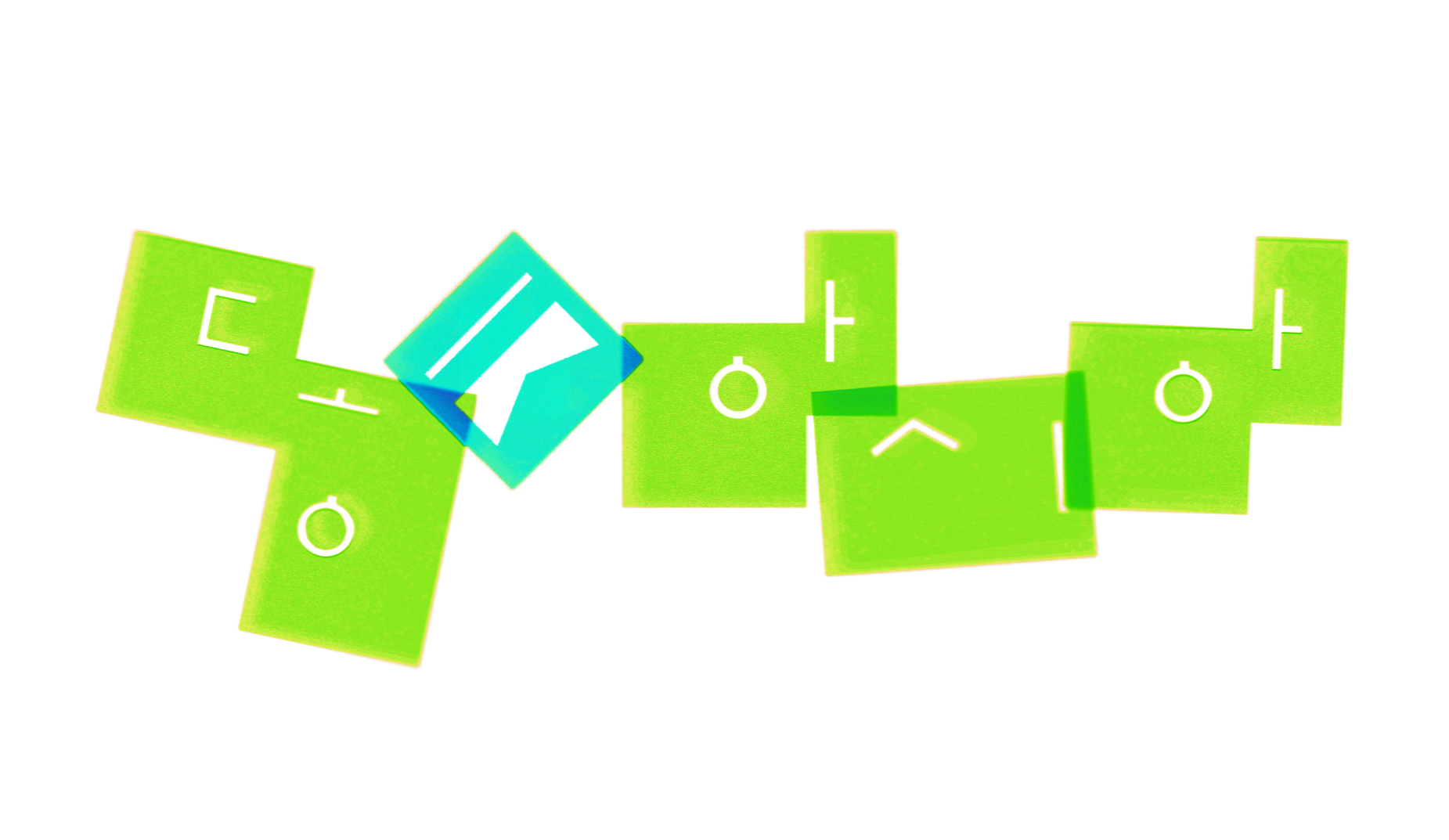
【동아시아(Asia) 친구들 문자와 함께 써요.】 〈친구체Chingu〉는 한자문화권 전각문자와 다국어 조판하기 위한 풀어쓰기 탈네모꼴 서체입니다. 한자문화권의 다른 전각 문자와 탈네모꼴 한글을 혼합조판 하기 위한 고민에서 시작합니다. 전각 공간과 탈전각 공간의 논리가 충돌해서 만드는 기분 좋은 노이즈를 만나보세요. 〈친구체Chingu〉는 이를 드러내기 위해 흑과 백을 반전한 블록(block)형 서체입니다. 또한 포함된 공백 글립을 통해 띄어쓰기 역시 블록으로 설정할 수 있습니다. 전각문자와의 다국어 조판이 필요한 포스터, 제목, 표지 등의 작업에 활용해 보세요. 이질성은 서로를 밀어내는 성질이 아닙니다. 문자가 만드는 관계의 아름다움!
친구체
Chingu
친구체는 한자문화권 문자와의 혼합 조판을 위해 설계된 전각·반각 모듈형 탈네모꼴 서체입니다. 탈네모꼴에서 탈의 대상을 획(흑)이 아닌 공간(백)으로 보면, 탈네모꼴 글자가 동아시아의 전각문자와 충돌하며 만드는 노이즈를 인식할 수 있습니다. 이 노이즈는 탈네모꼴 한글과 전각문자의 사이의 관계를 형성합니다. 친구체는 이 지점에서 탈네모꼴 한글과 한자문화권 전각 문자 사이의 새로운 관계성을 드러낸 서체입니다. 이러한 주제의식을 블랙 바탕의 블록 구조로 풀어내어 탈네모꼴 공간의 해석을 표현했습니다. 또한 전각·반각의 블록이 한자나 가나가 놓일 수 있는 글줄 흐름선을 만들어줍니다. 전각의 구조와 탈 전각의 구조가 함께 작동하도록 한 것입니다. 서로 다른 문자 체계가 각자의 이질성을 유지한 채 맺는 아름다움으로, 창의적인 다국어 타이포그래피 작업이 가능합니다.
【탈네모꼴】에서 탈의 대상을 획이 아닌 공간으로 보면, 탈네모꼴 한글과 전각문자의 관계성이 보입니다. 〈친구체Chingu〉는 이를 드러내기 위해 흑과 백을 반전한 블록(block)형 서체입니다. 전각·반각 블록이 만드는 거친 획의 질감과 기하학적인 한글의 표현이 매력적입니다. 이 서체는 한글 11,172자, 라틴 52자, 기호 활자 160자를 지원합니다. 첫 스케치는 홍익대학교 타이포그래피(Typography) 소모임 한글꼴연구회 2025 가을전 《다람쥐 헌 쳇바퀴에 타고파》에서 공개되었습니다. 이후 추가적인 작업을 거쳐 2026년 AGFont에서 출시된 후, 〈탈네모틀 한글 발표회〉에서 작업 과정과 생각을 공유했습니다.
문자 체계간의 【노이즈】는 독서의 방해 요소가 아닙니다. 적절한 시각적 노이즈는 각 문자 체계의 구분력을 더하고, 타이포그래피(typography)의 기능적 요소로 활용할 수 있습니다. 따라서 문자의 특성과 그것이 활용되는 맥락을 이해하고 그것에 맞는 편안한 디자인 환경을 제시하는 것이 중요합니다. 〈친구체Chingu〉는 다국어 조판 환경에서 한자문화권의 다양한 문자와 섞이고, 동시에 한글만의 독창성과 성격을 유지합니다. 디자이너는 건강한 마음으로 문자의 성격을 관찰하고 이해하여, 정보를 다루고 매체(media)에 탑승시킬 때에 활용하여야 합니다.